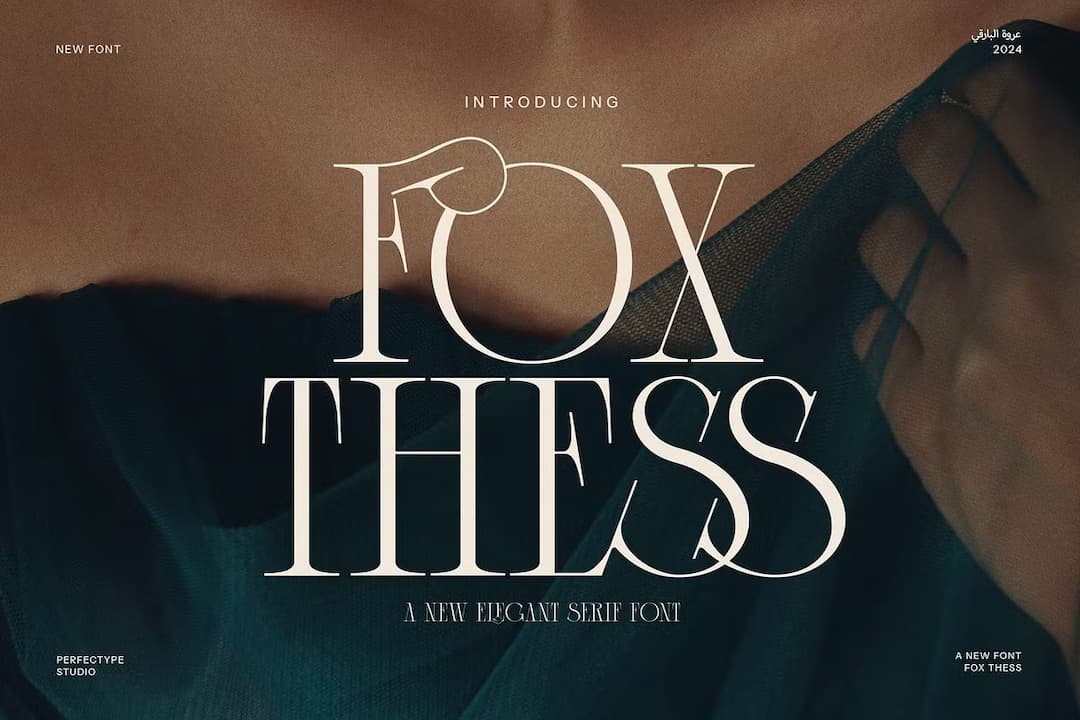
Fox Thess
本日は童話『ごんぎつね』の作者、新美南吉の誕生日(1913)だそうなのでこちら。リガチャーがおもしろいクラッシーなモダンローマンディスプレイ。繊細で腰高なモダンローマンをベースに、ユニークなリガチャーを多数持った書体。まあ最近よくあるっちゃよくあるタイプ。基本的なグリフ自体は割とスタンダードで奇妙に変形した文字はないが、リガチャーの仕方がにゅよっとしたカーブが隣のグリフに食い込むという変わったやり方をしていておもしろい。小文字はなく大文字のみ。1ウェイト。ちなみに筆者はごんぎつねを読んだことはない(笑)。教科書になかったんだよね…